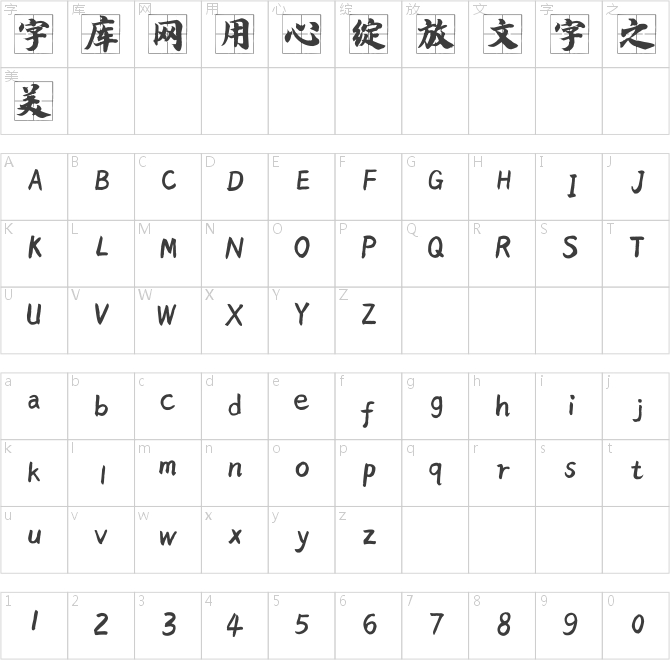
漢呈王天喜古風(fēng)體
漢呈王天喜古風(fēng)體字體字庫(kù)是一款讓人賞心悅目、百看不厭的中文字體,適合各類廣告和產(chǎn)品包裝設(shè)計(jì)應(yīng)用,字體大小5.42MB,格式為ttf字體,上傳用戶是漢呈字庫(kù),作者/版權(quán)方為漢呈字庫(kù)